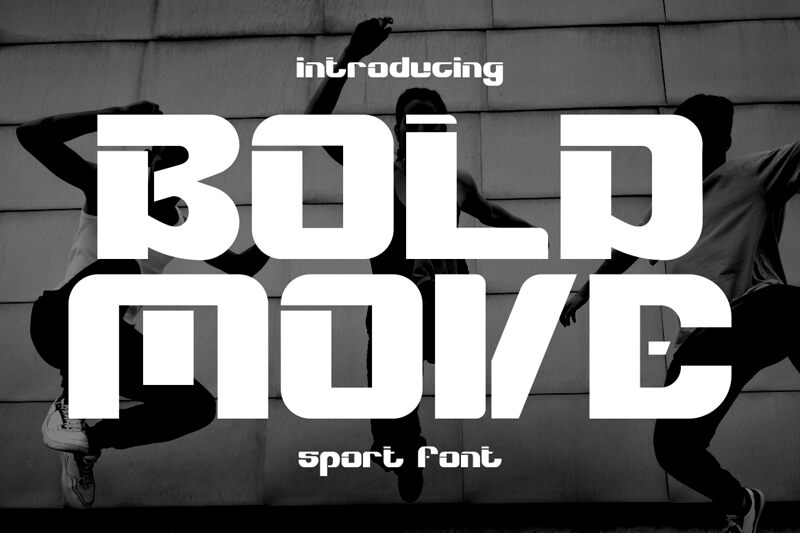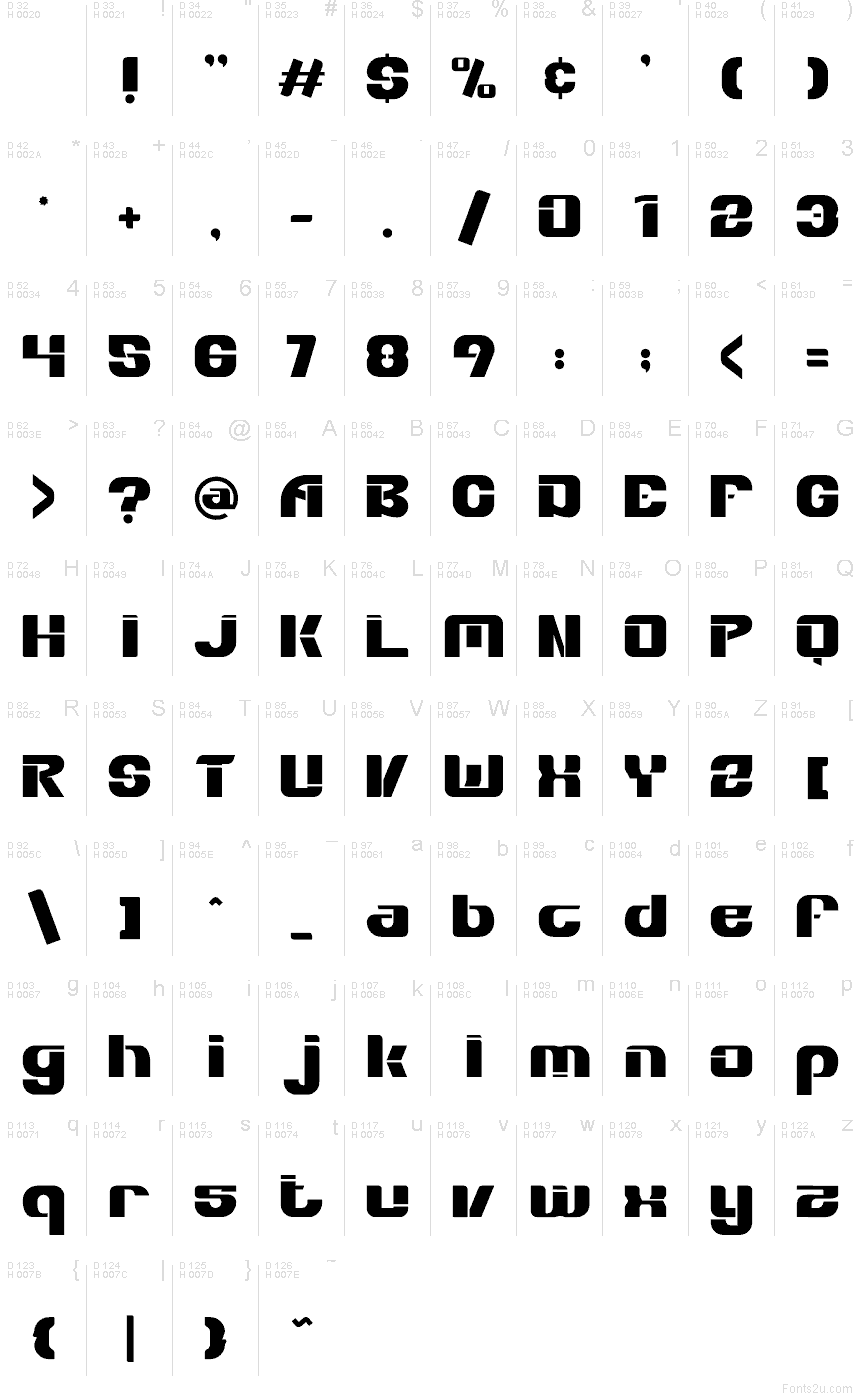
Bold Move
Bold Move od Shanaf Studio je bezplatné zaoblené technické písmo typu display s masívnym, takmer futuristickým charakterom. Písmená pôsobia, akoby boli zostavené z veľkých blokov s mäkkými hranami, so širokými krivkami, štvorcovými otvormi a ostrými rezmi, ktoré dodávajú písmu mechanický rytmus namiesto hravosti.
Prirodzene zapadne do brandingu hier, hudobných plagátov, úvodných obrazoviek aplikácií, streetwearovej grafiky a titulkov, kde krátke slová vyžadujú výrazný digitálny mood. Ako bezplatný font sa hodí aj na obálky, skice log a hlavičky na sociálne siete, najmä ak hľadáte husté, kompaktné písmo, ktoré vyzerá konštruovane, ale stále plynule.